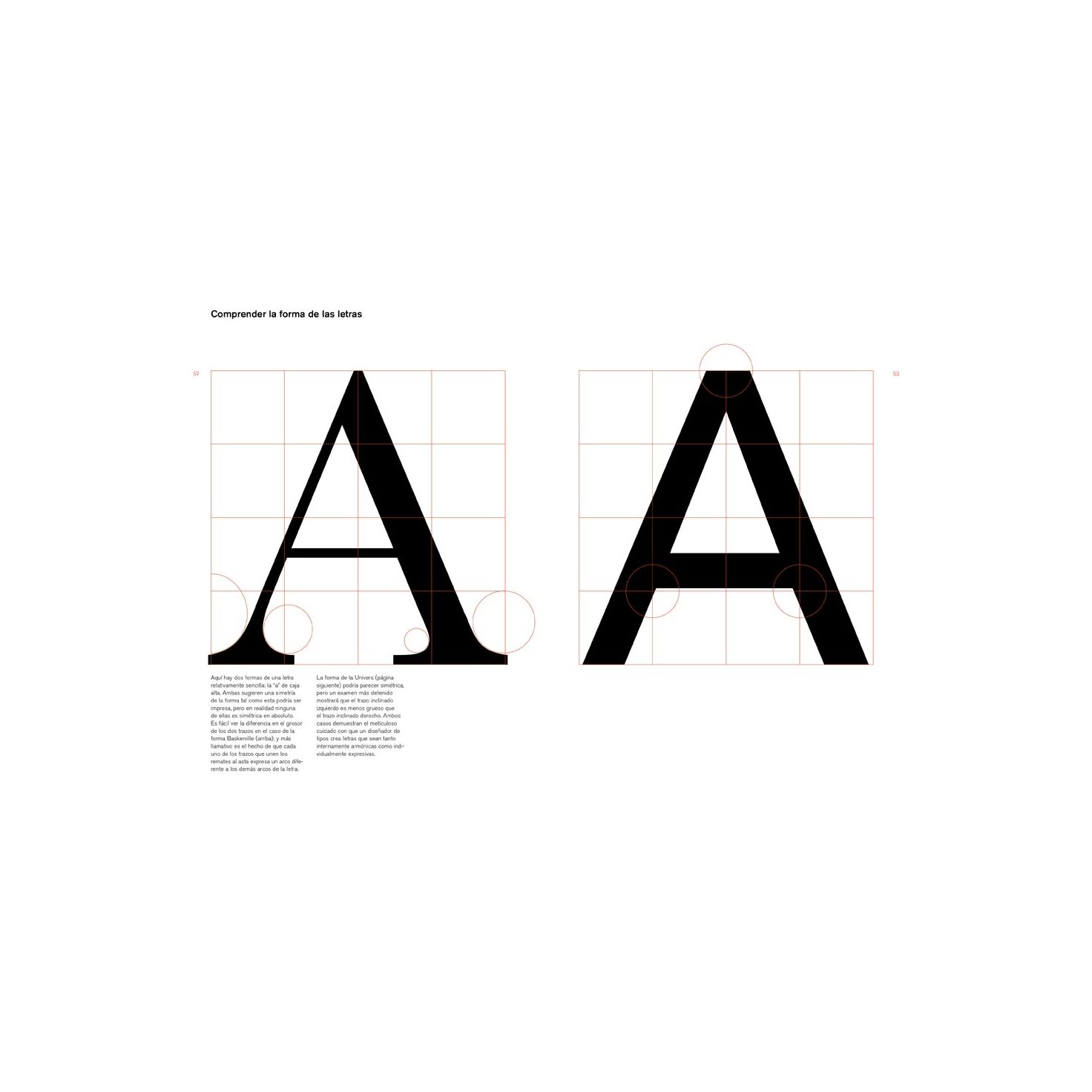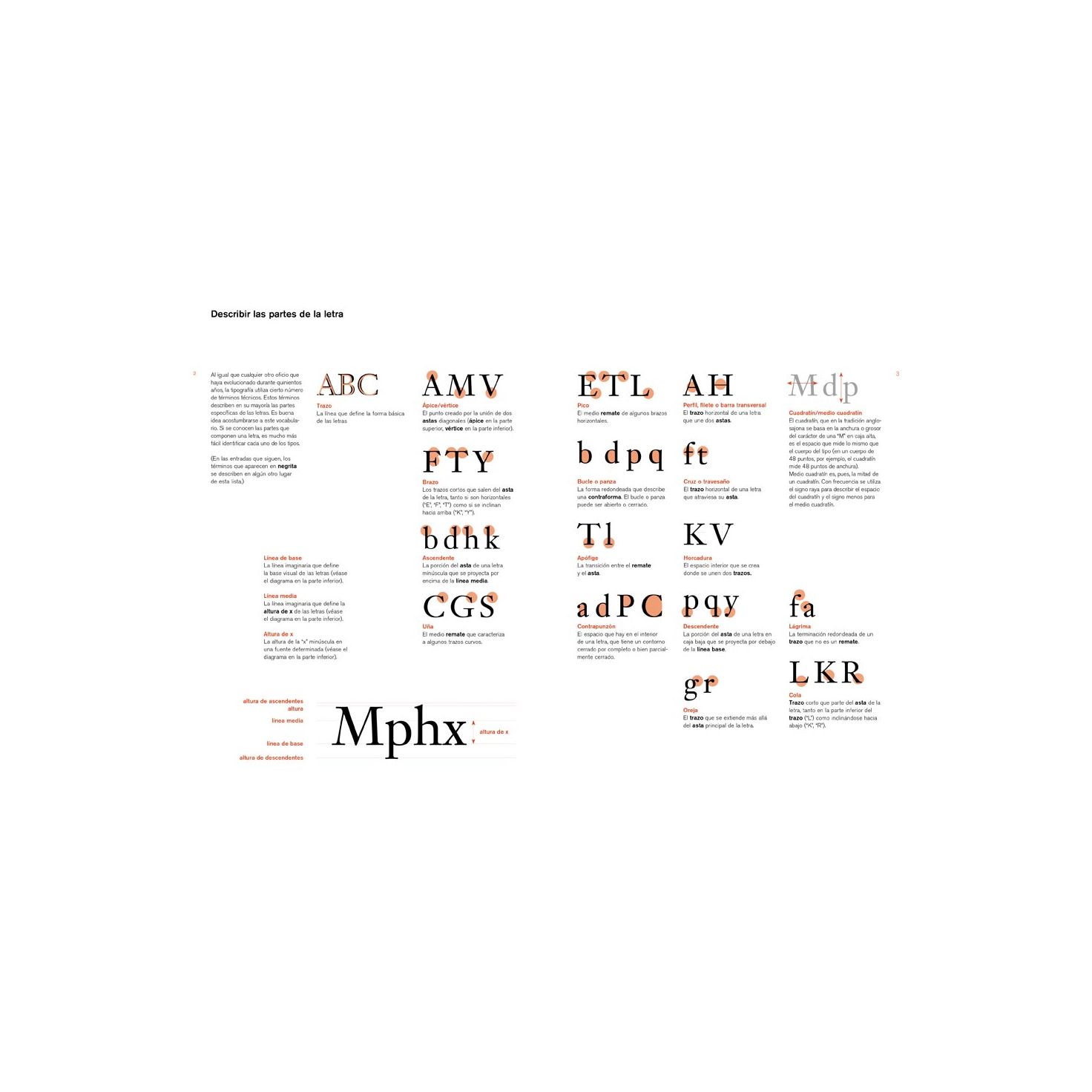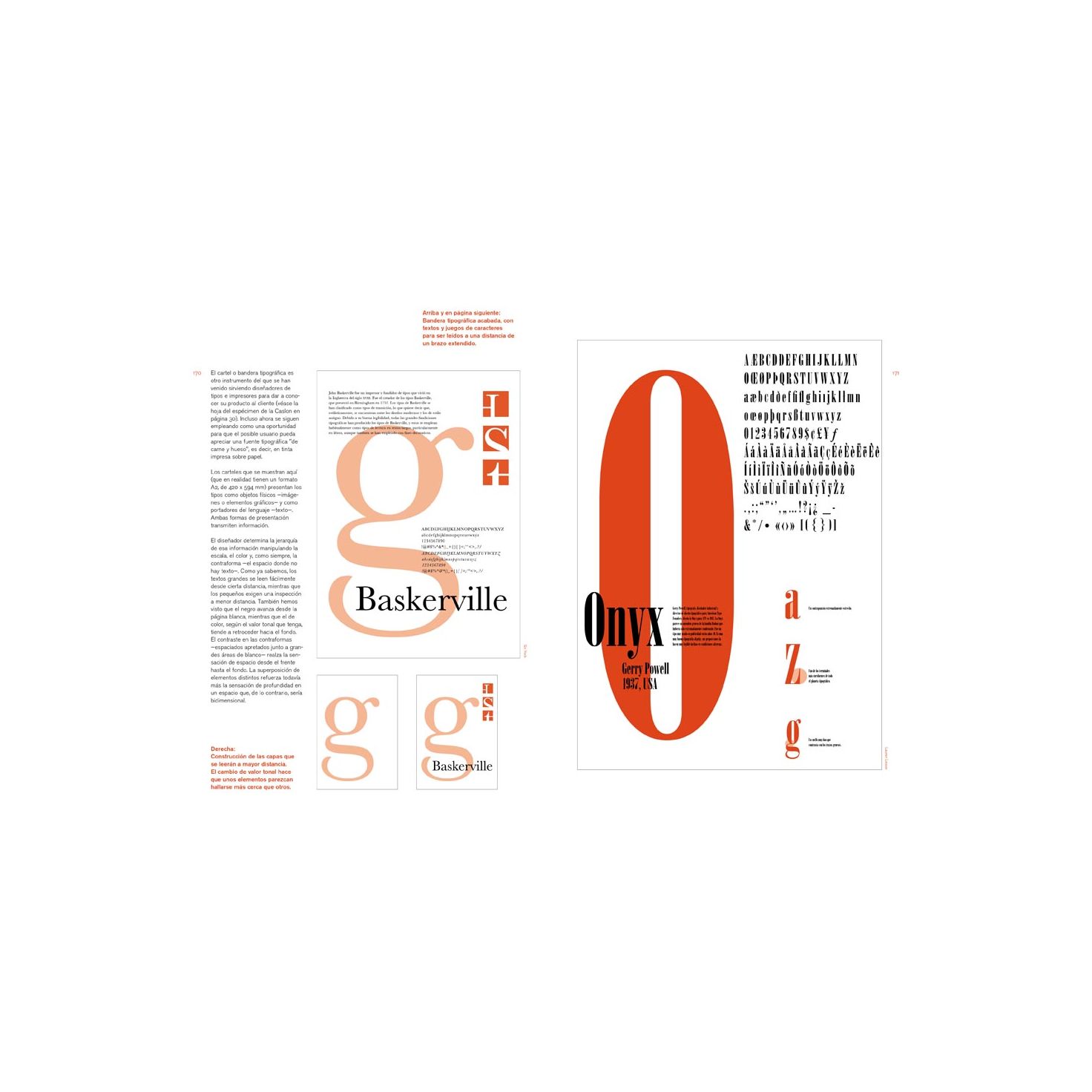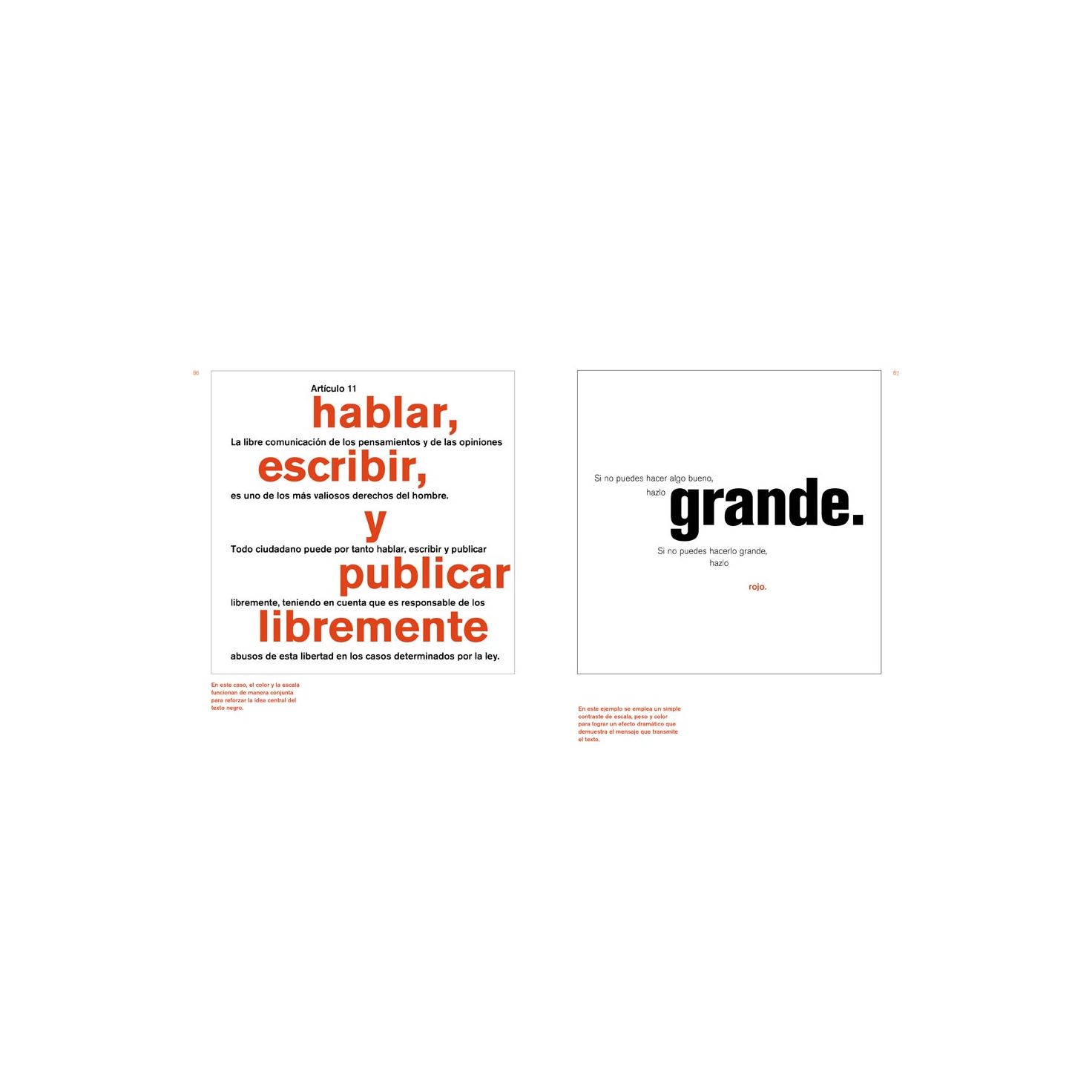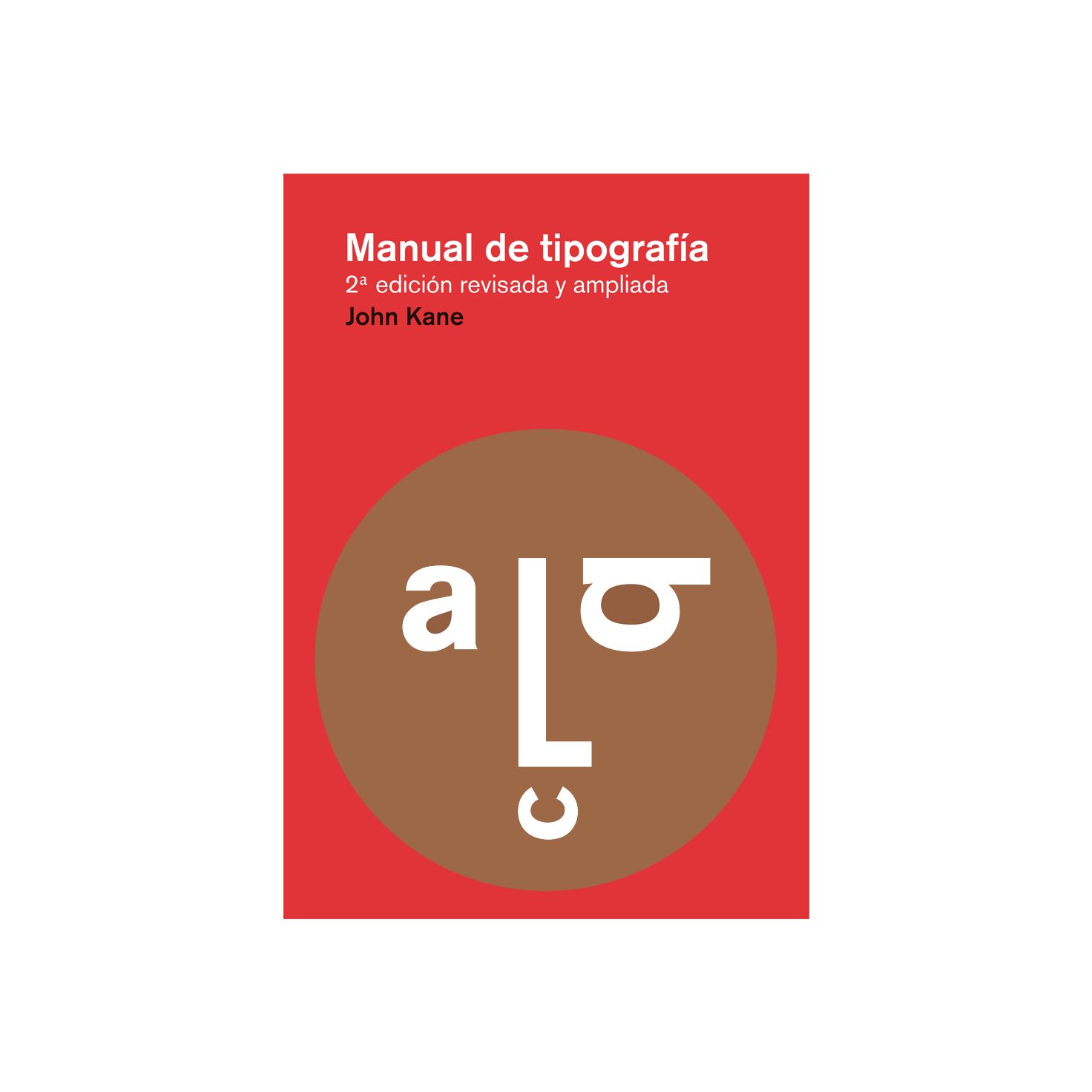
Manual de tipografía
Este Manual de tipografía es una introducción a todo lo que cualquier estudiante o profesional del diseño gráfico debe saber sobre tipografía para desarrollar una sensibilidad y unos conocimientos tipográficos bien fundamentados.
El libro expone los principios básicos de la tipografía y principales aplicaciones mediante una equilibrada combinación de historia, teoría y práctica. Así, el lector encontrará en estas páginas desde la descripción de las partes de la letra o la clasificación de los diferentes tipos, a la explicación de cómo se compone el texto en la página o cómo funcionan los sistemas de retículas. Pero también encontrará una breve y reveladora historia de la tipografía así como numerosos ejemplos y ejercicios prácticos que pretenden ayudar a adquirir un conocimiento experiencial de la disciplina.
Esta segunda edición revisa algunos contenidos de la primera e incorpora nuevos diagramas explicativos y nuevos materiales sobre la composición de textos, la elección de tipos y el uso del color. El libro se apoya además en un nuevo sitio web —www.atypeprimer.com (en inglés)— que alberga materiales adicionales y una serie de ejercicios prácticos.